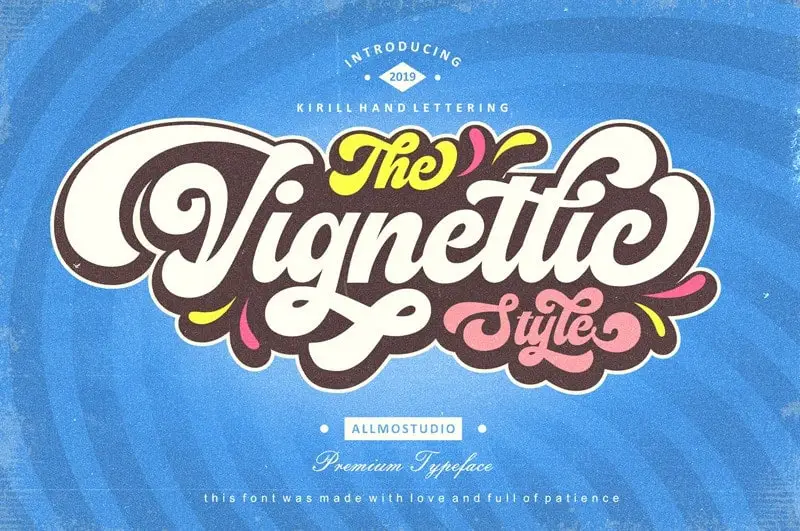
Vignettic Script Font – Download Grátis
Esta fonte é uma script semifinalizada que foi projetada para logotipos, apresentando um tom atraente com elementos retro, moderno e vintage. Foi criada pelo designer movefont na 99designs. Vignettic traz influências dinâmicas do design de sinais e broches, inspiradas em cultura ativa. Além das letras maiúsculas e minúsculas, numerais e símbolos de pontuação, a fonte também oferece muitas variações por caractere, incluindo alternativas de opentype. Seja você designer gráfico ou profissional de marketing digital, Vignettic Script é uma escolha ideal para aqueles que buscam um toque único e versátil em seus projetos.